Transforme sua inspiração em tipografia
Aprenda a transformar imagens de referência em imagens gráficas para seus projetos de ilustração tipográfica
A ilustração tipográfica existe há séculos; as iniciais em xilogravura encontradas em livros e bíblias medievais são alguns dos exemplos mais antigos. Algumas foram criadas com tantos detalhes que são pequenas obras de arte por si só.
Combinar tipografia e ilustração é uma técnica que pode ser usada para chamar a atenção e enviar uma mensagem de forma poderosa. Pode transformar o significado de uma palavra porque, dessa forma, você não está apenas lendo, mas também visualizando.
“Quando você começa a ilustrar palavras, você adiciona mais sentimento a elas”, diz Birgit Palma (@birgitpalma), uma artista austríaca especializada em ilustração e letras que vive em Barcelona. E acrescenta: "Você pode fazer uma palavra ganhar força, mas também pode destruí-la, dependendo do tipo de ilustração que usar". A tipografia ilustrada envia uma mensagem subliminar com muito impacto.
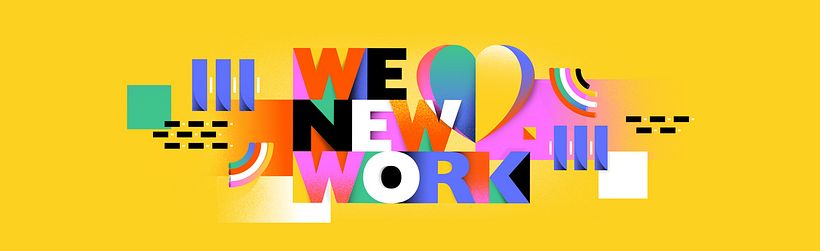
Birgit já trabalhou com grandes clientes como Adidas, Adobe, Diesel, Hyundai ou Coca-Cola e explica como pegar algumas imagens de referência como fonte de inspiração e transformá-las em novas ideias, que você pode converter em material gráfico para incorporar ao seu texto.
Crie o mood board
Birgit usa como exemplo o projeto para criar uma tipografia modular para uma cidade. Depois de escolher a cidade (no caso, Tóquio), Birgit cria um mood board repleto de imagens de referência, incluindo as principais atrações turísticas (Monte Fuji e o trem-bala), arte e o trabalho de alguns designers japoneses.
A seguir, Birgit cria duas listas: uma com nomes referentes à cidade e outra com adjetivos. Essas listas ajudam a definir a essência da cidade e os adjetivos desenham suas emoções. Birgit normalmente escolhe um nome da lista e o associa a um dos adjetivos, fazendo um rápido esboço de cada combinação.
Não interprete as imagens literalmente!
Birgit busca uma forma de reinterpretar essas ideias e torná-las mais abstratas e, portanto, únicas. Nas litografias El Toro, Picasso se desafia tentando testar o quão longe pode ir removendo detalhes da imagem para criar interpretações abstratas do touro. “Ao realizar este processo, você tem que se perguntar o quanto quer que sua criação se pareça com a imagem de referência. Como você vai fazer com que as formas que desenhe interpretem a ideia de suas imagens de referência, mas de uma maneira mais divertida”, sugere Birgit.
Tente capturar emoções
Para explicar este conceito. Birgit examina um estudo de Kandinsky, no qual a artista recria uma abstração pura a partir dos movimentos de uma dançarina em uma série de fotografias. Assim, ele interpreta o movimento com uma série de linhas e círculos.
Você pode ver este método aplicado em outras obras dele. “Kandinsky estava tentando incorporar a emoção dos dançarinos em seu trabalho artístico. E é exatamente isso que eu quero fazer”, diz Birgit. E acrescenta: "Em vez de interpretar literalmente, pense na emoção, na essência, que é a camada um pouco mais profunda. Tente reproduzir isso".
Preste atenção aos detalhes importantes
Você pode prescindir de detalhes e cores. Simplifique a imagem. Depois de se livrar das informações desnecessárias, pode começar a brincar com formas e cores.
Desmonte a estrutura em partes simples
Charley Harper faz muitos desenhos de animais. Na análise de seu trabalho, Birgit mostra como começa trabalhando o corpo através de uma forma simples e, depois, acrescenta pequenos detalhes que identificam o animal, antes de terminar com alguns elementos decorativos. Embora esta última etapa não seja essencial.